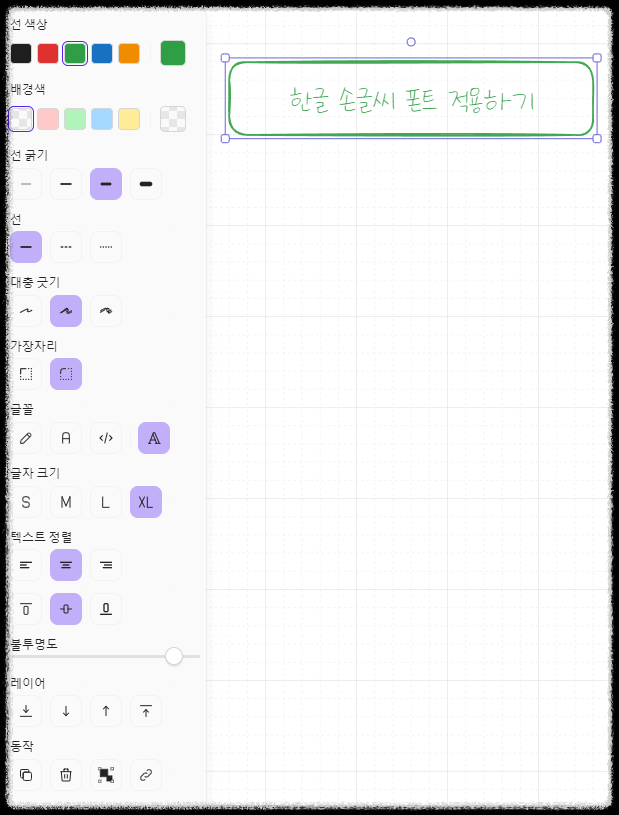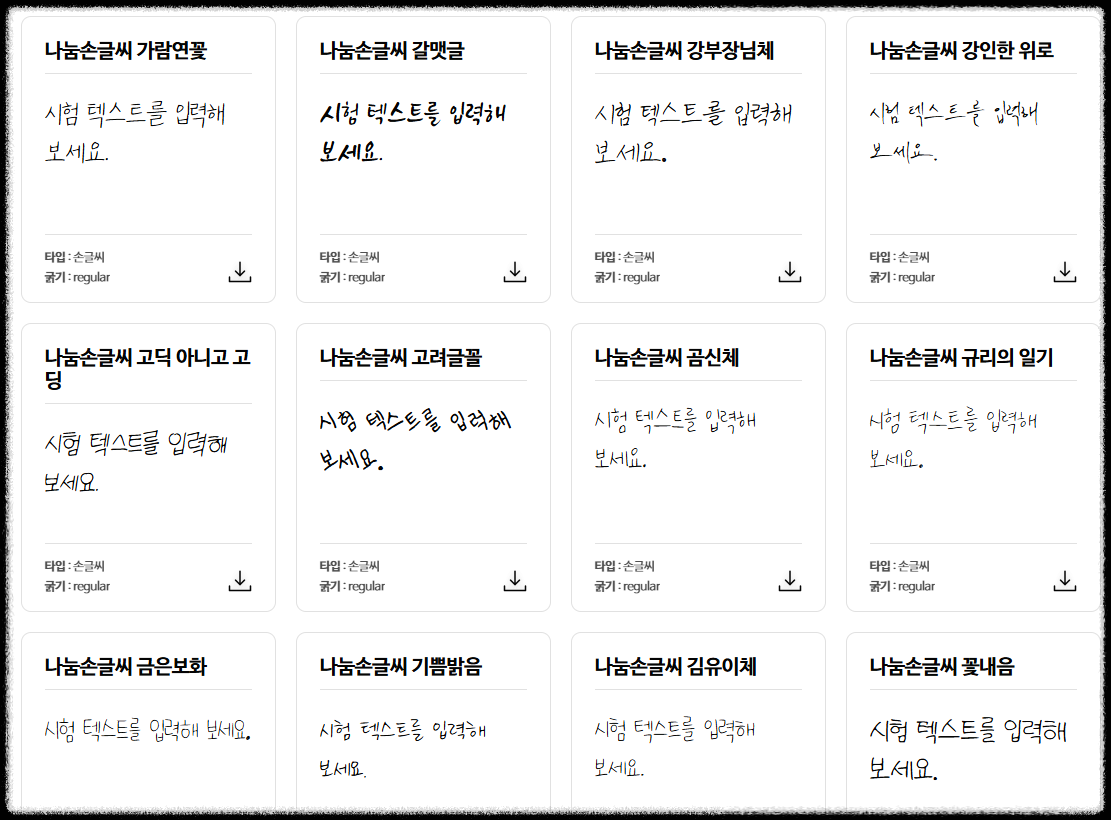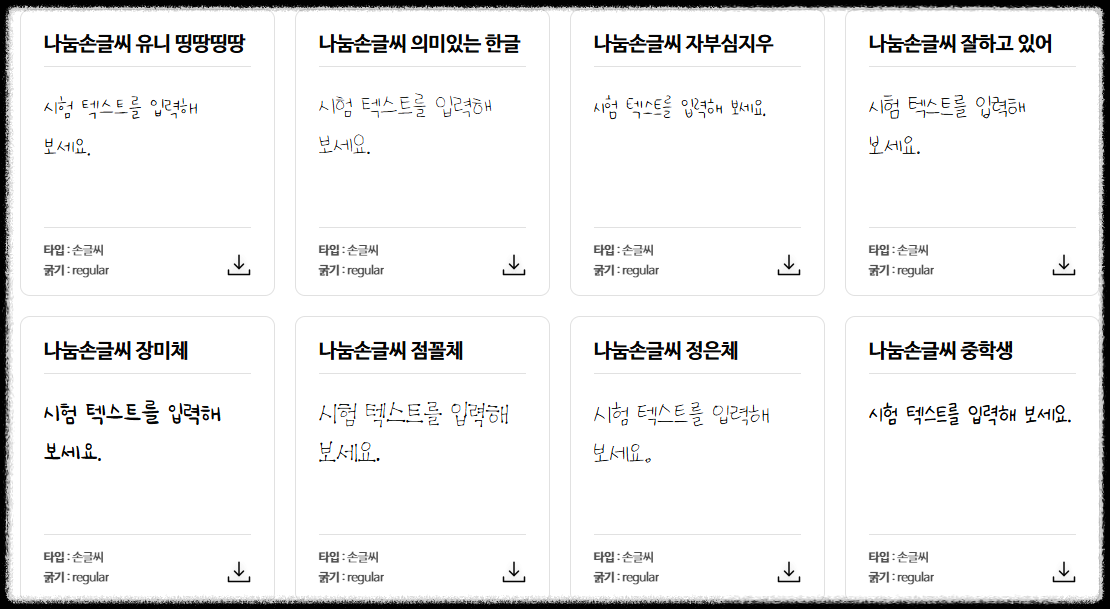
옵시디언 엑스칼리드로우 Excalidraw 시각화 | 한글 손글씨 폰트 적용하기
옵시디언의 엑스칼리드로우 Excalidraw 플러그인은 간단한 스케치부터 복잡한 다이어그램까지 자유롭게 그릴 수 있는 시각화 도구다.
기본적으로 제공되는 폰트도 충분히 유용하지만, 뭔가 부족한 감이 있다. 한글 필기체처럼 독특한 글꼴을 사용해 좀 더 개성 있는 다이어그램을 만들 수 있다면 좋지 않을까.
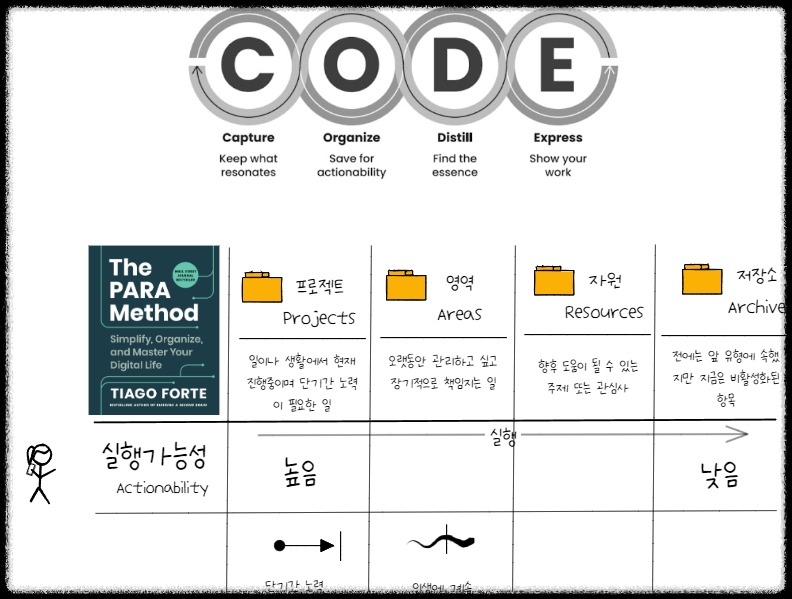
여기서는 옵시디언 엑스칼리드로우 Excalidraw에서 원하는 한글 손글씨 폰트를 적용하는 방법을 단계별로 설명해 보겠다.
먼저, 사용할 손글씨 폰트를 다운로드해야 한다. 네이버에서는 클로바 나눔 손글씨 시리즈라는 무료 글꼴을 제공하며, 필기체 스타일이 다양해 원하는 폰트를 선택할 수 있다.
이제 엑스칼리드로우 Excalidraw에서 한글 필기체를 활용해 더욱 독창적인 다이어그램과 노트를 작성할 수 있다. 손글씨 폰트를 사용하면 다이어그램이 손으로 그린 듯한 느낌이 더해져 개성 있는 표현이 가능하다.
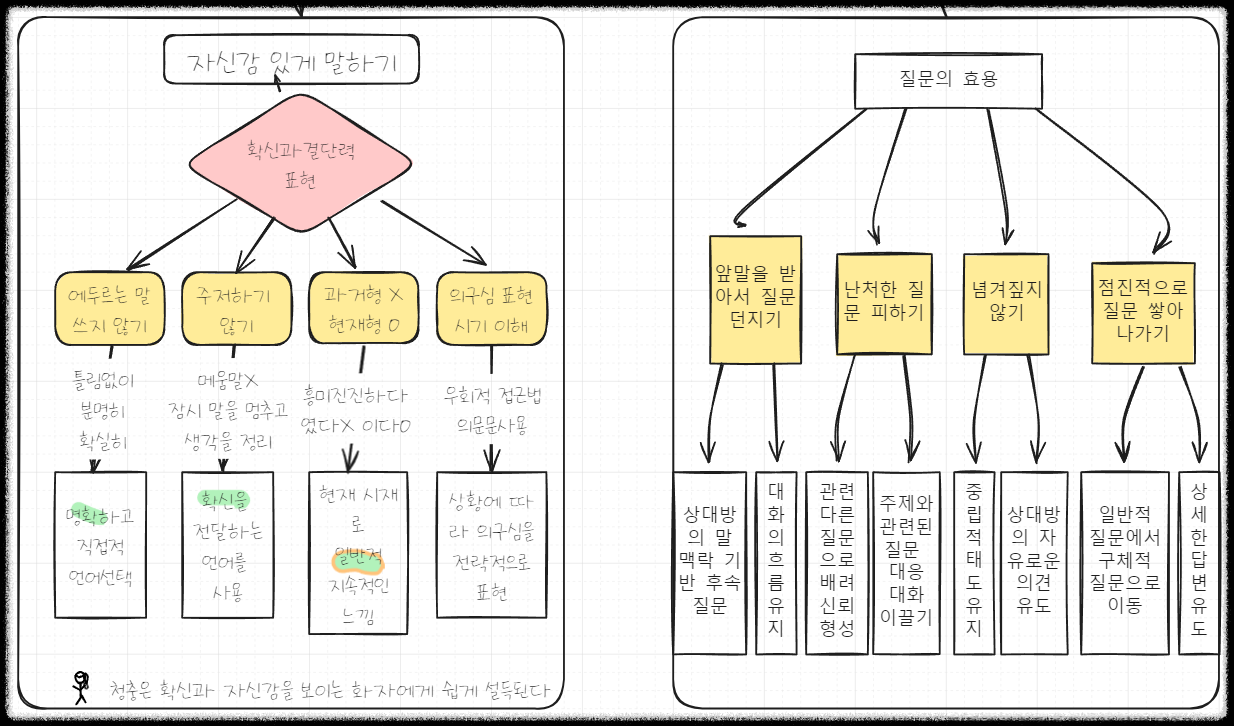
옵시디언 엑스칼리드로우 Excalidraw에서 한글 손글씨 폰트를 적용하는 방법을 살펴보았다. 한글 폰트를 사용하면 더욱 자연스럽고 친근한 느낌을 전달할 수 있어, 학습 노트나 아이디어 스케치에 적합하다. 엑스칼리드로우 Excalidraw의 유연한 기능과 옵시디언의 강력한 노트 시스템을 결합해 더 멋진 다이어그램을 만들어보자.